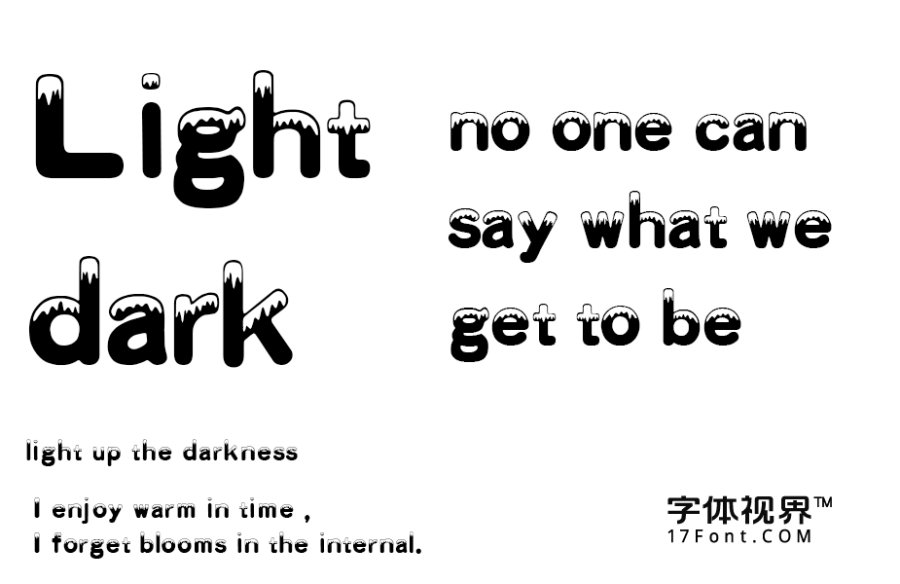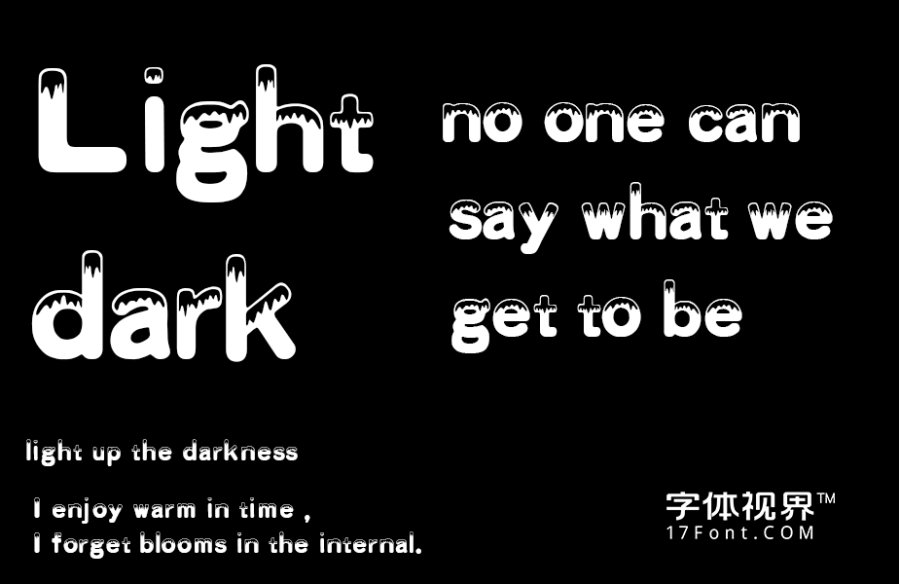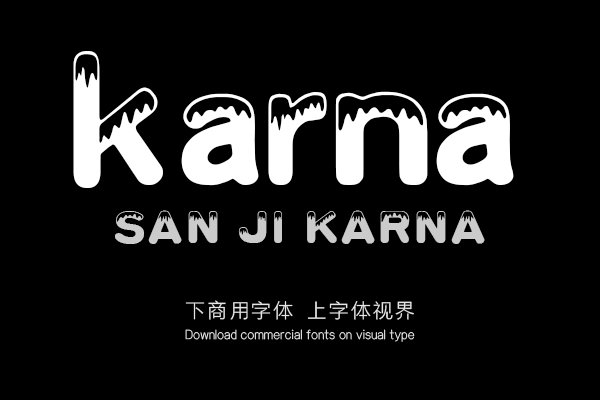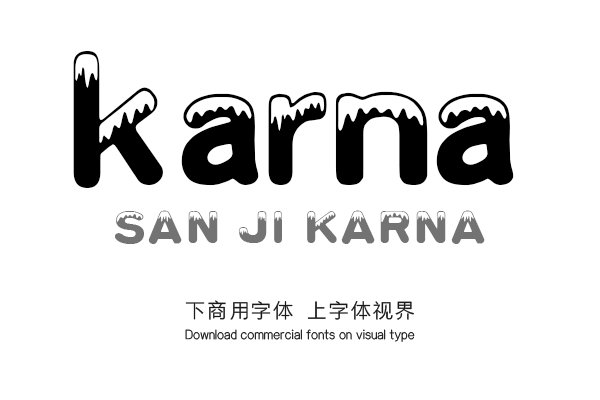
Karna字体为立体字,有积雪效果,黑白对比强烈。字形结构丰满。适用于广告,包装,报纸印刷,屏幕显示。购买须知:“下载服务费”与“字体VIP”所获得字体 仅用于个人非商用, 商用请联系付费授权。本字体为电脑用字,手机没有root权限不支持直接手机换字(手机如何root,请自行百度搜索教程)。购买前请先 了解清楚后再付款 ,字体为虚拟产品无法回收 一旦购买不支持退款。